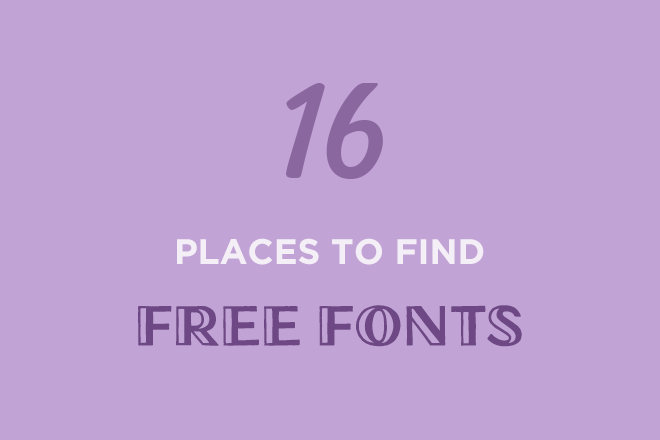
Классные варианты шрифтов для придания индивидуальности вашему веб-дизайну
Выбор шрифтов для сайта - это важный аспект веб-дизайна, который может повлиять на восприятие и узнаваемость вашего сайта. В данной статье вы найдете полезные советы и идеи для выбора уникальных и стильных шрифтов, которые подчеркнут индивидуальность вашего сайта и привлекут внимание пользователей.
Прежде всего, учтите тематику вашего сайта и его целевую аудиторию. Если ваш сайт ориентирован на публику молодежи, подойдут современные и экспериментальные шрифты с необычными начертаниями.
Используйте сочетание нескольких шрифтов для создания выразительного дизайна. Комбинируйте шрифты разных стилей - жирный с легким, серифный с беззасечным. Это добавит динамики и глубины вашему контенту.
Не забывайте о читабельности шрифтов. Даже самый стильный и уникальный шрифт может быть непригодным для использования на сайте, если он плохо читается. Тестирование читабельности шрифтов на разных устройствах и размерах экранов - это неотъемлемая часть процесса выбора шрифтов.